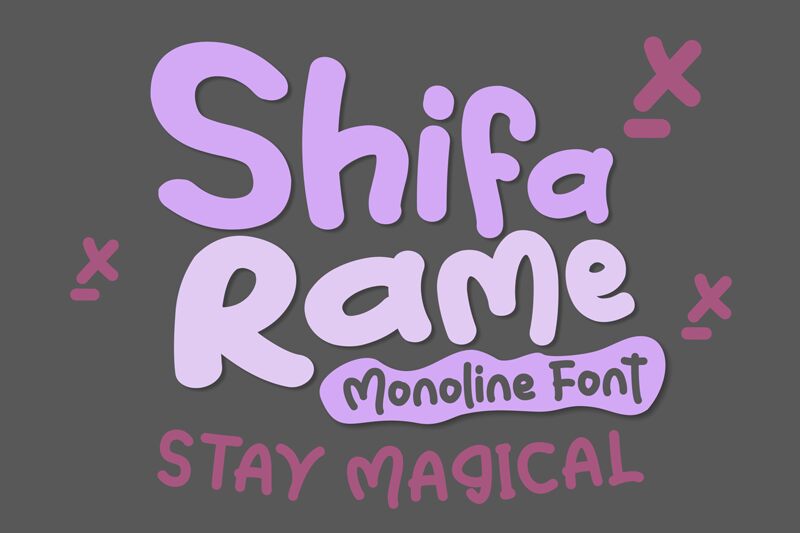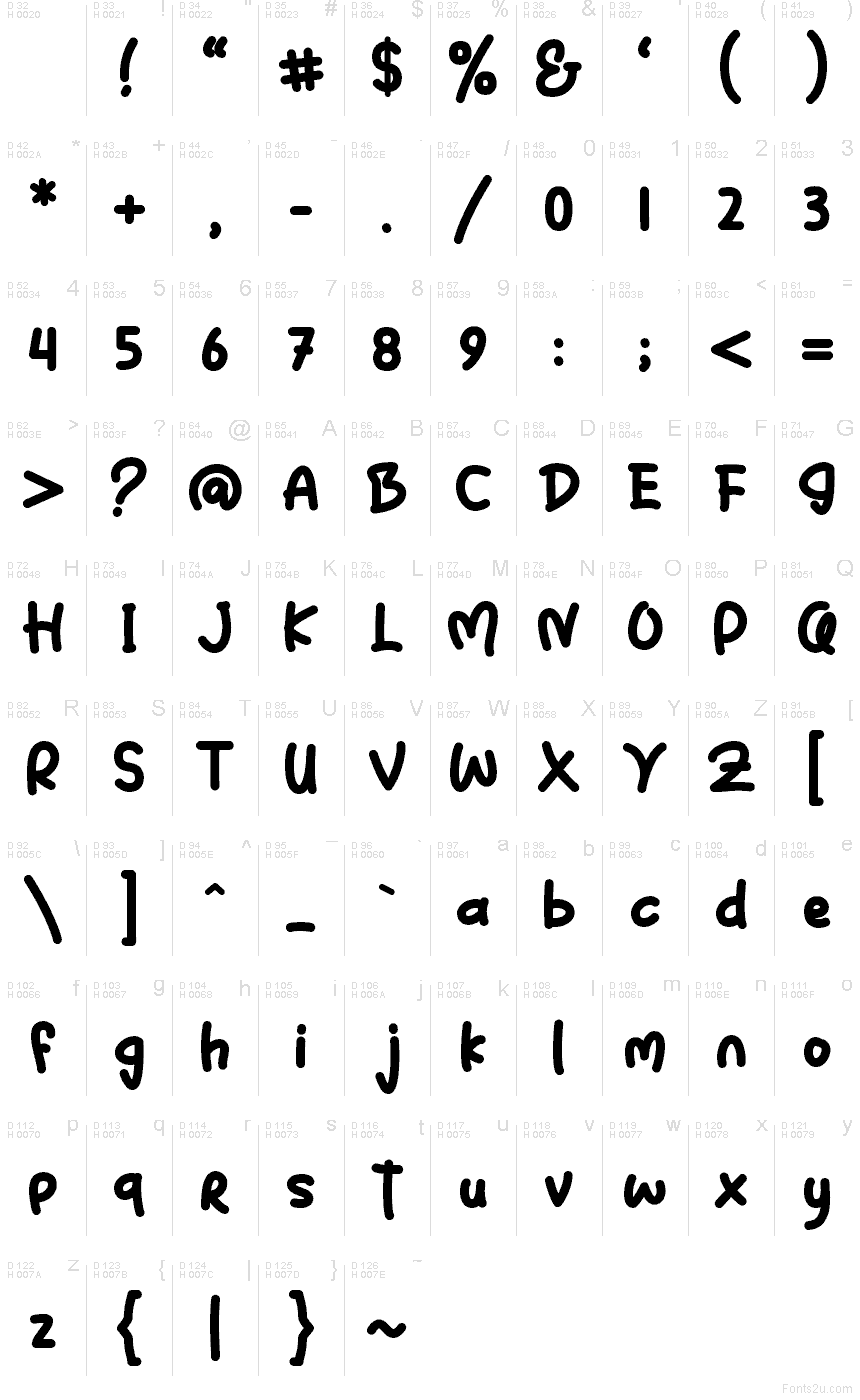
Shifa Rame, créée par Mabhal Studio, est une police de caractères de type « comic » gratuite, qui se distingue par son aspect doux et dessiné à la main. Ses lettres sont rondes et conviviales, dotées d'extrémités arrondies, de traits épais irréguliers et d'un rythme libre qui confère au texte un esprit décontracté plutôt que trop formel.
Elle est idéale pour tous vos projets nécessitant une voix légère et chaleureuse : emballages de produits pour enfants, menus de cafés, designs d'autocollants, publications sur les réseaux sociaux et image de marque ludique. Utilisez cette police gratuite pour des titres courts, des lignes d'accroche, des cartons-titres ou de grands noms, là où ses courbes généreuses et ses jointures légèrement irrégulières peuvent s'exprimer pleinement.